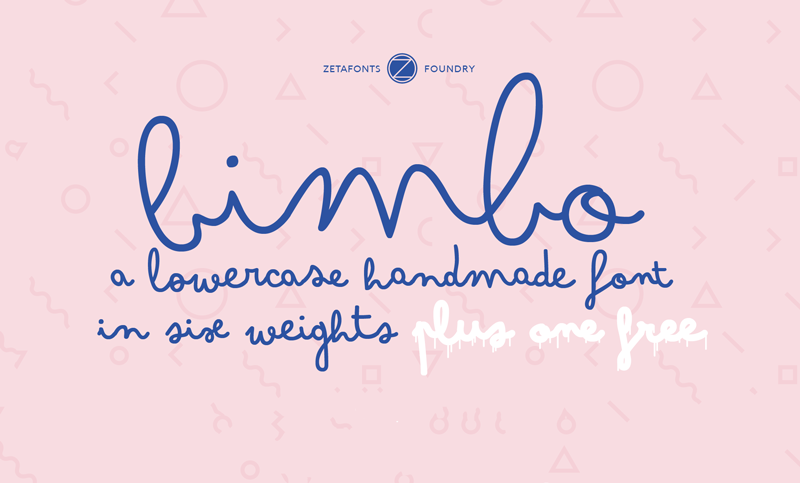
Bimbo Script Font – Download Grátis
A fonte Bimbo é uma família de tipo script monoline criada por Francesco Canovaro para a Zetafonts em 2018. Ela expandiu a designação original Arsenale White, um tipo de arteisil italiano criado pelo ilustrador Jonathan Calugi. Essa nova fonte adicionou seis novos pesos e mais de 300 caracteres adicionais que cobrem cerca de setenta idiomas usando alfabetos latino, grego e cirílico. Isso mantém a estética handmade que tornou o original fonte bem-sucedido. Para designers gráficos, a Bimbo é uma excelente escolha para manter seu design moderno com um toque de sofisticação e diversidade linguística.